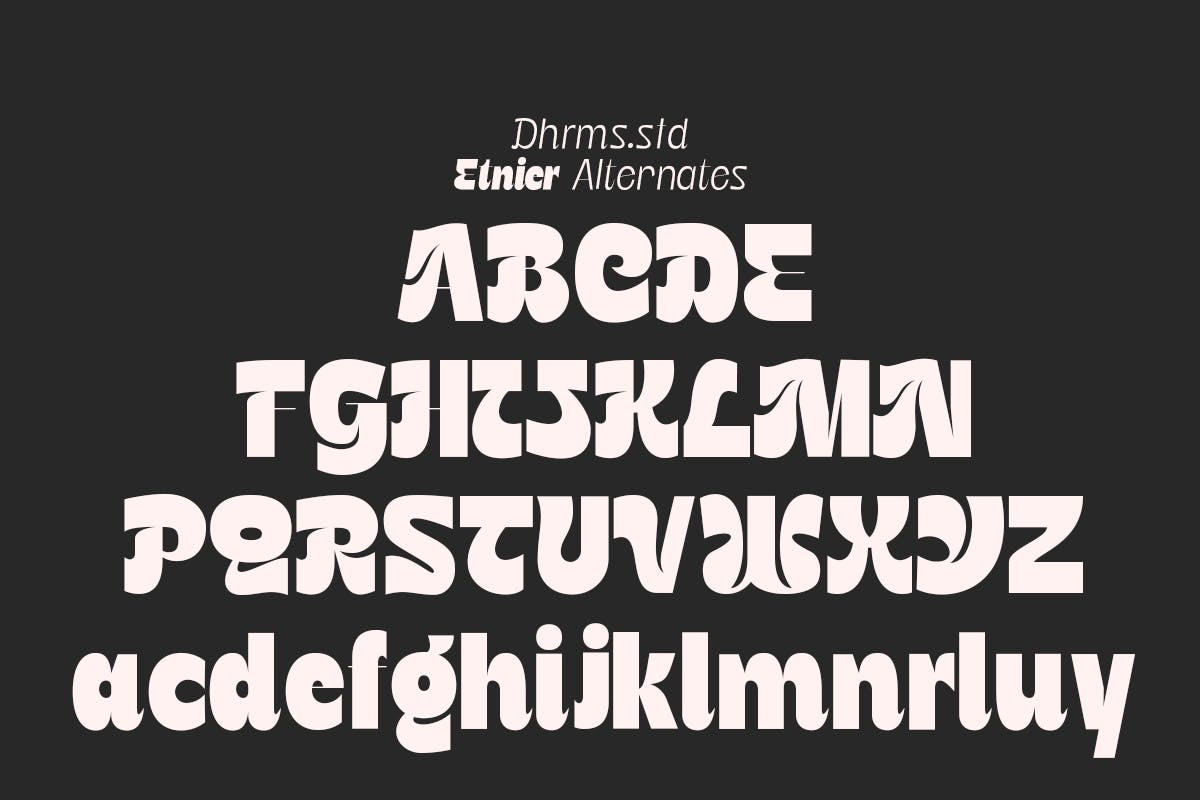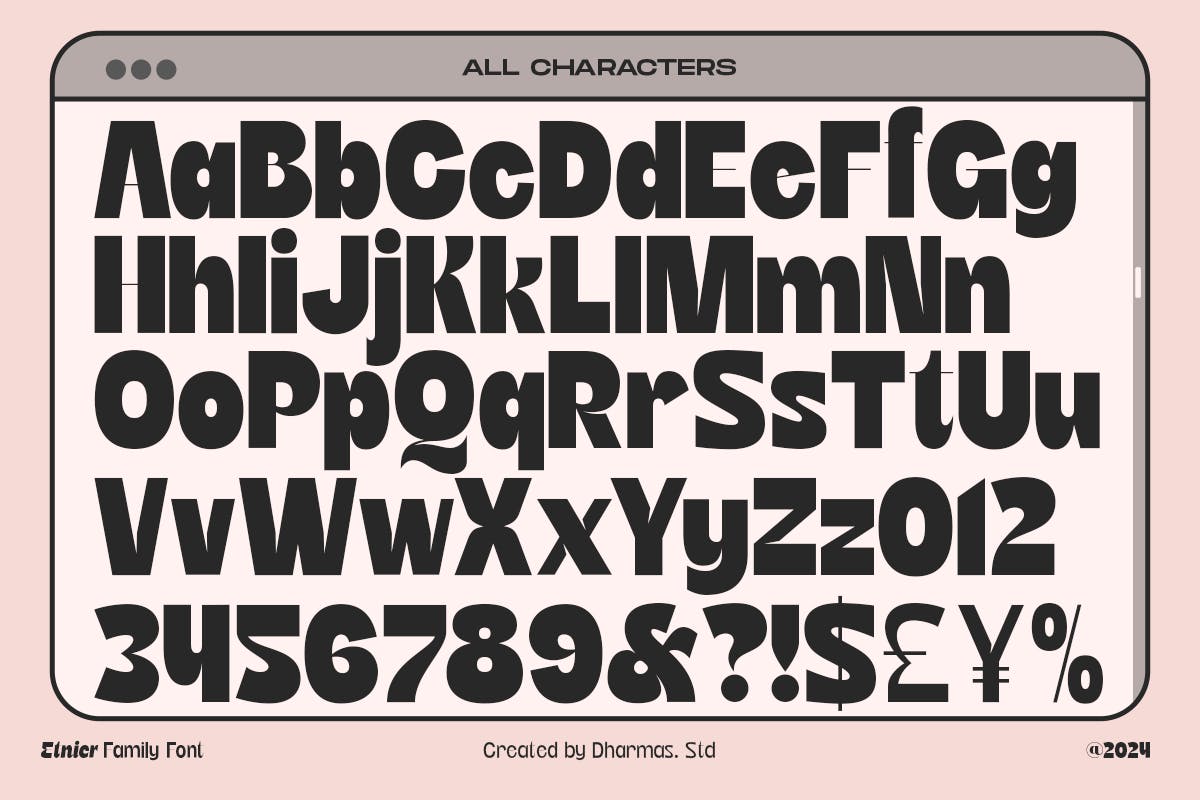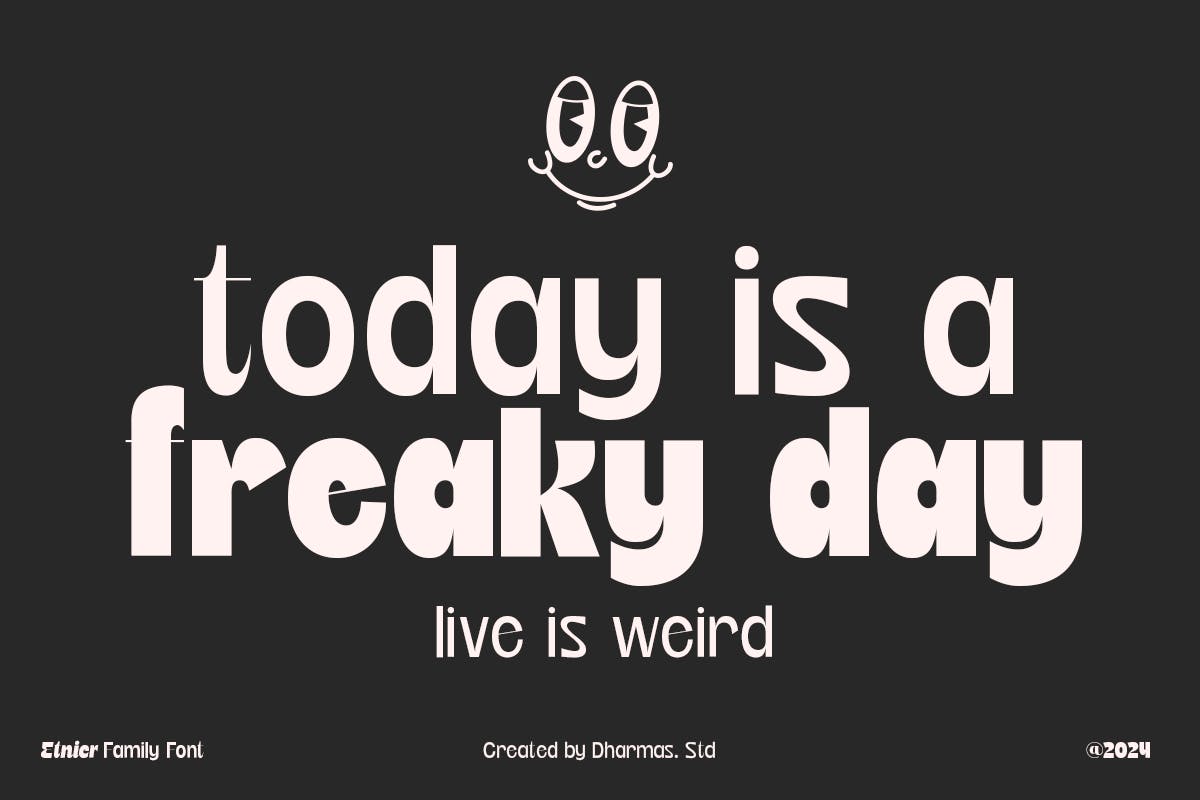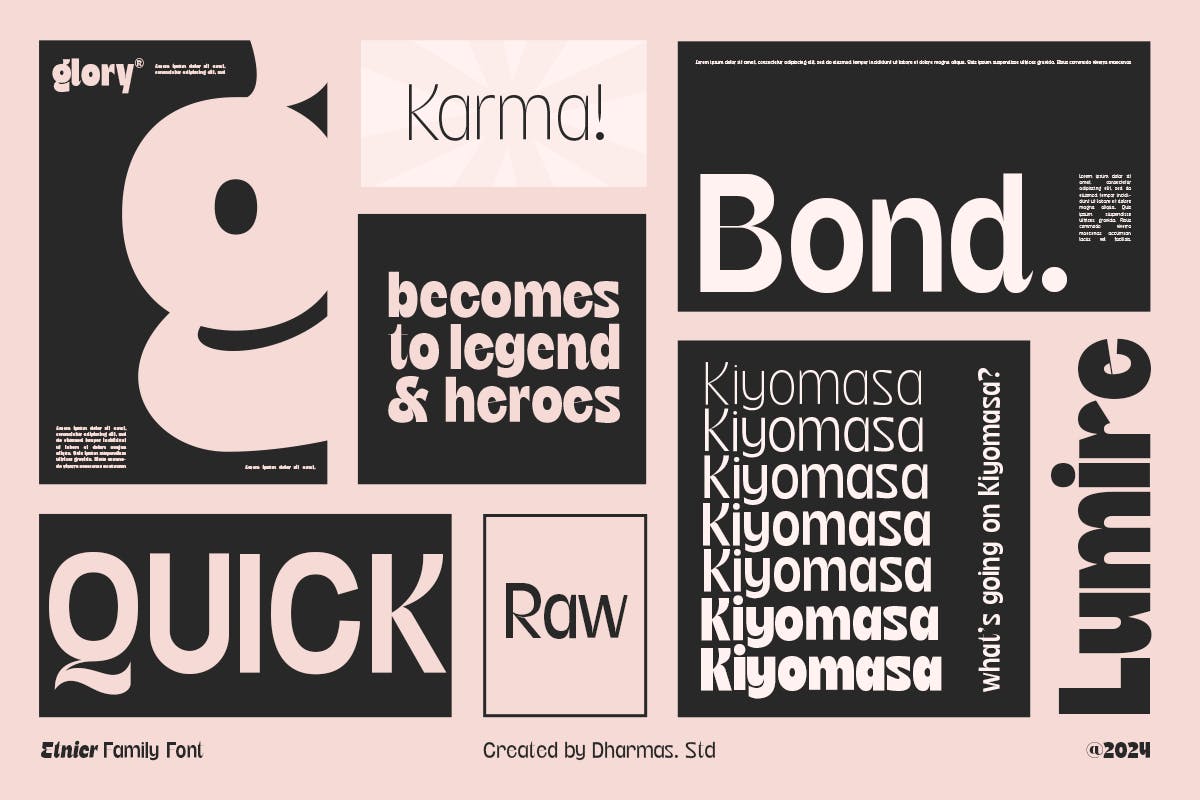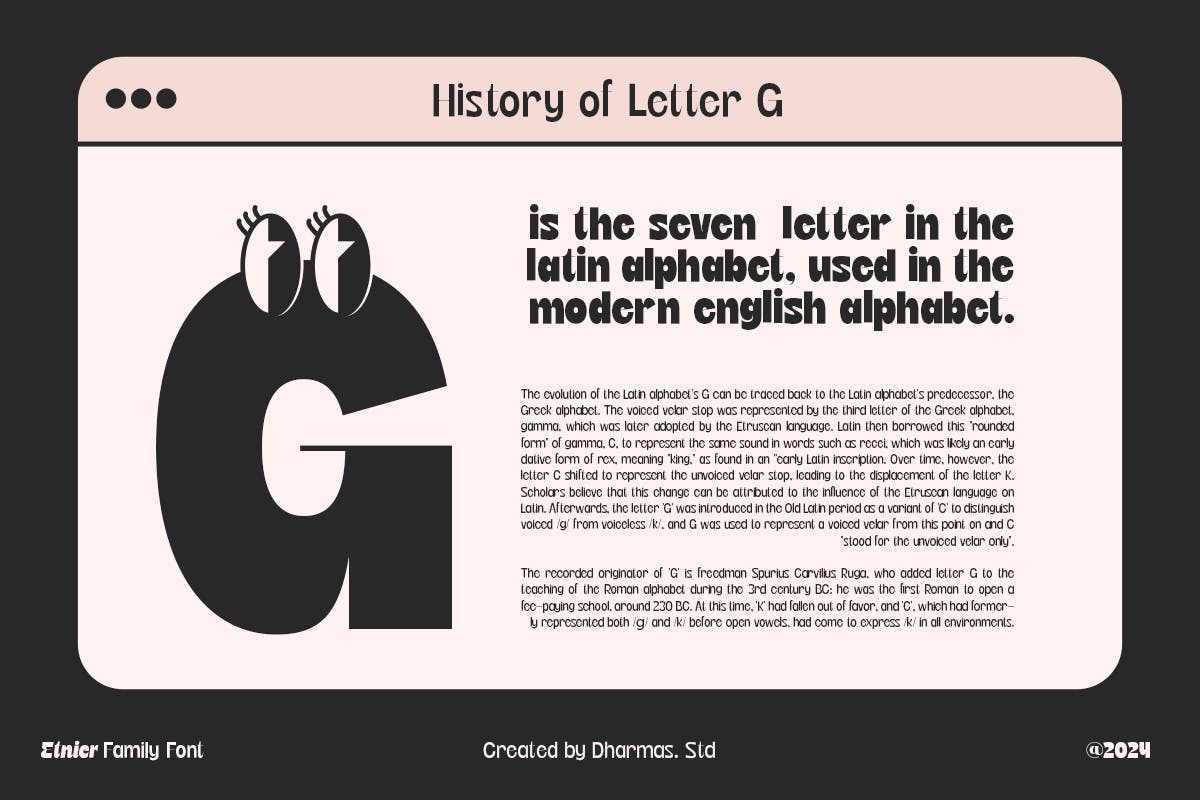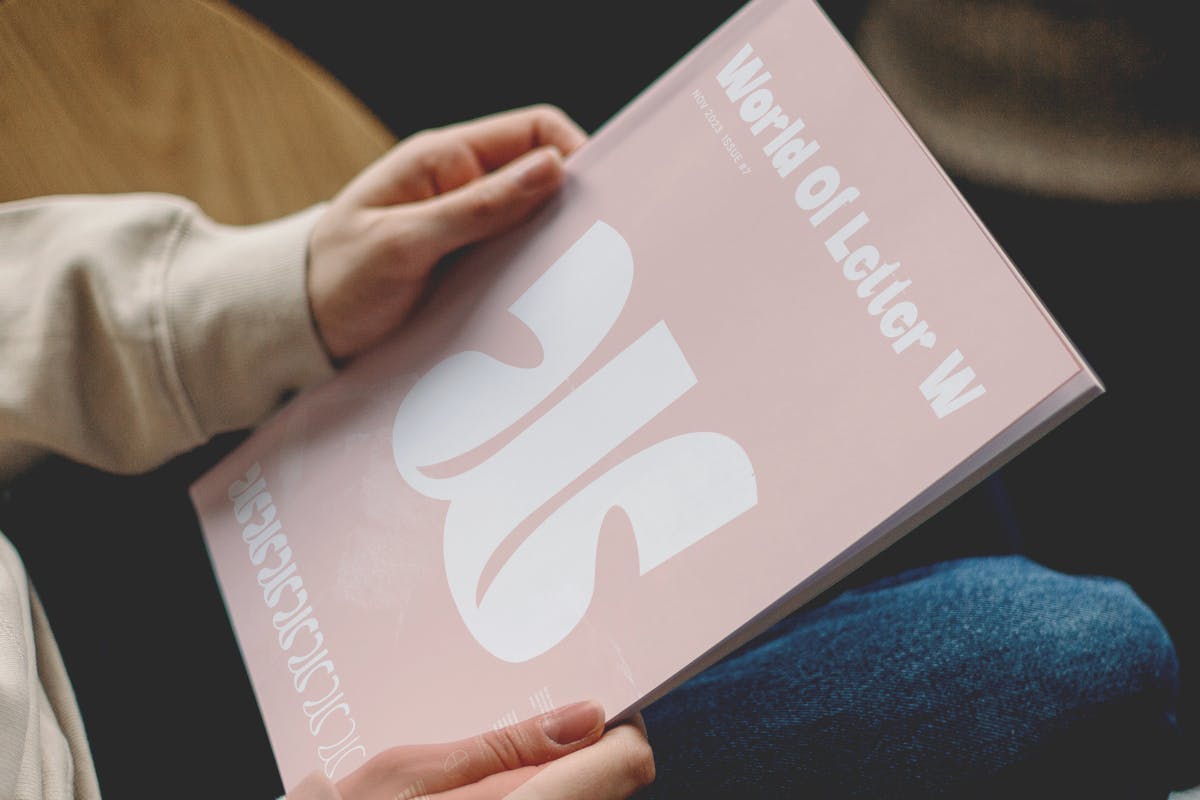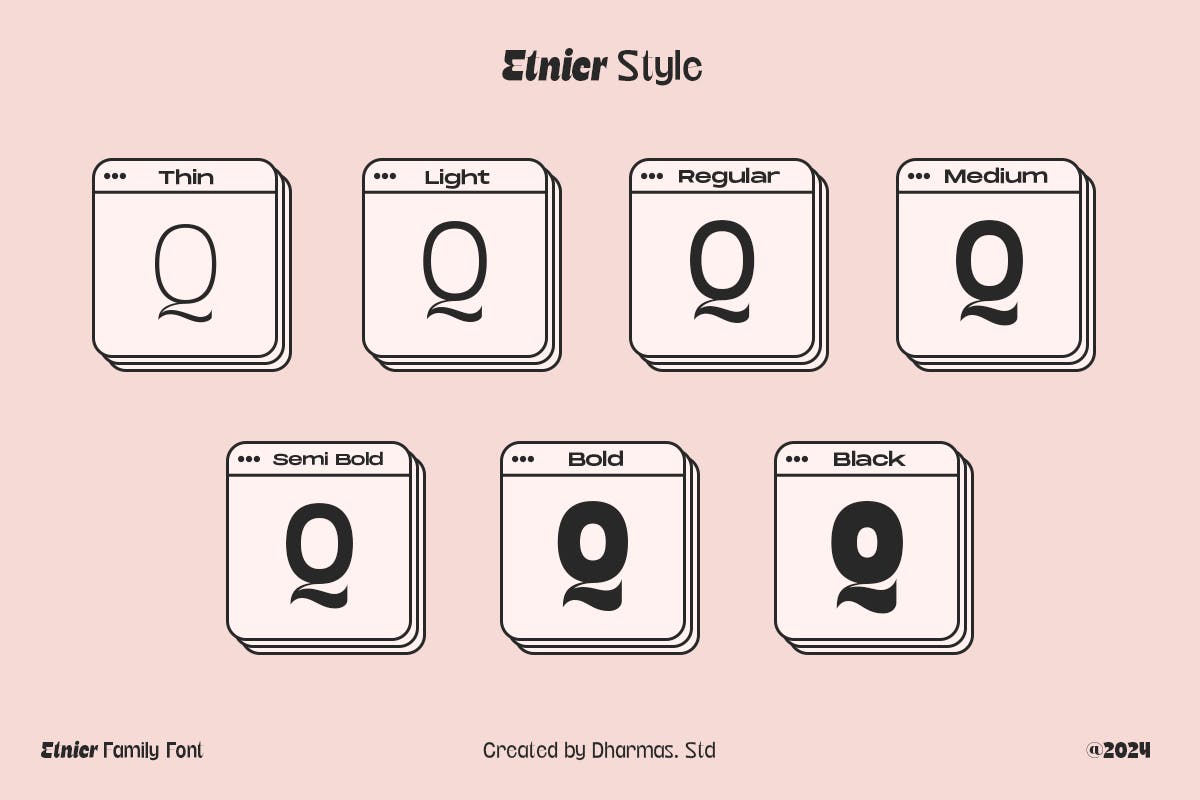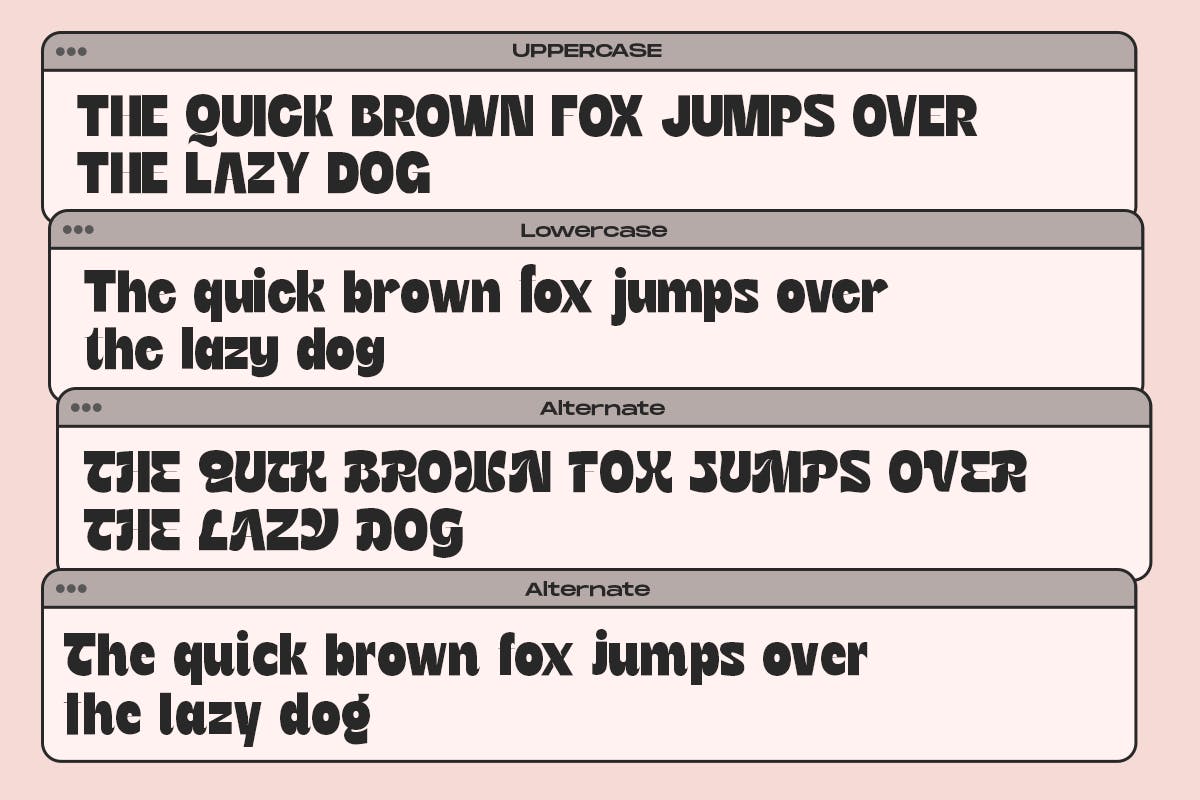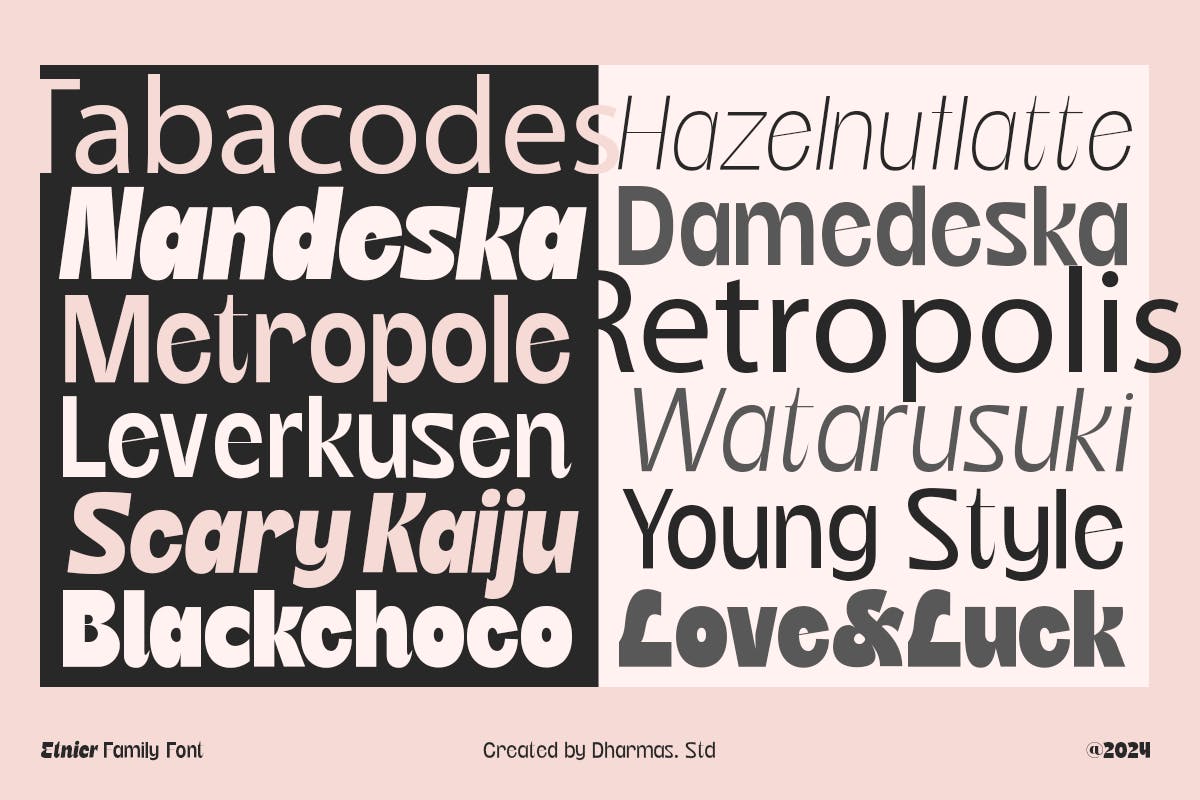
معرفی Etnier – یک خانواده مدرن و جدید با طراحی منحصر به فرد!
Etnier یک فونت متغیر مدرن است. در واقع، این فونت sans-serif با ظاهری محکم و مربعی شکل، قابلیت خوانایی عالی را تضمین میکند. این فونت گزینههای مختلفی از لحاظ عرض و ایتالیک را ارائه میدهد که برای طراحیهای شما انعطافپذیری بالایی فراهم میکند. هر چه Boldتر، قویتر – این ویژگی Etnier است. خصوصیات Bold و مستحکم آن، به ویژه در نسخه ایتالیک، این فونت را برای طراحیهای مرتبط با UI/UX ایدهآل میسازد.
در مجموع، 14 استایل فونت در فایلهای OTF، TTF، WOFF و حتی بیشتر در صورت استفاده از فایلهای متغیر موجود است. شما این انعطاف را دارید که بین گزینههای وزن و عرض حرکت کنید تا بهترین حالت Etnier را پیدا کنید!